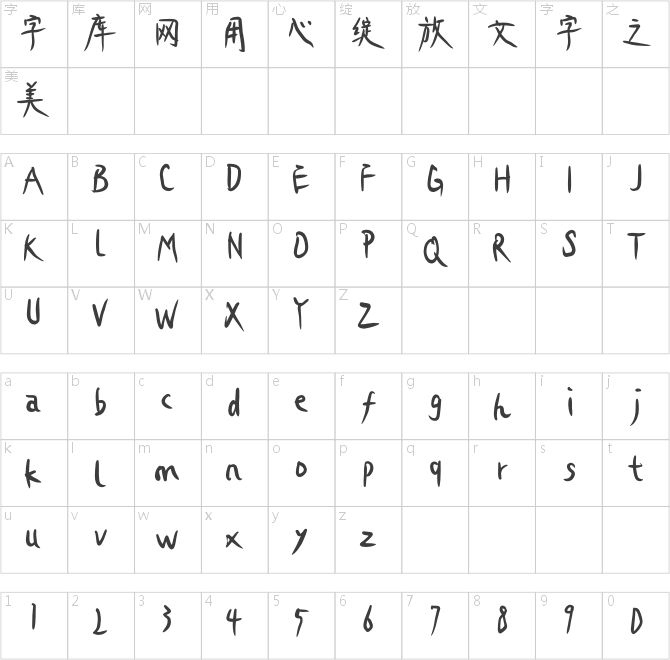
字体名称: 造字工房失乐体
造字工房失乐体
造字工房失乐体,字形舒展灵动。笔画粗中带细、错落有致、收放有度。整体风格紧中见放,简淡秀润。字体中大量弧线的应用,令其更显婉转流畅,给人以酣畅潇洒之感,有极强的视觉表现力。适用于大标题及个性品牌设计推广等环境。本字体为简体字库,采用OpenType/CID格式,Adobe-GB1-5编码,基于中华人民共和国GB2312-80字符集标准。